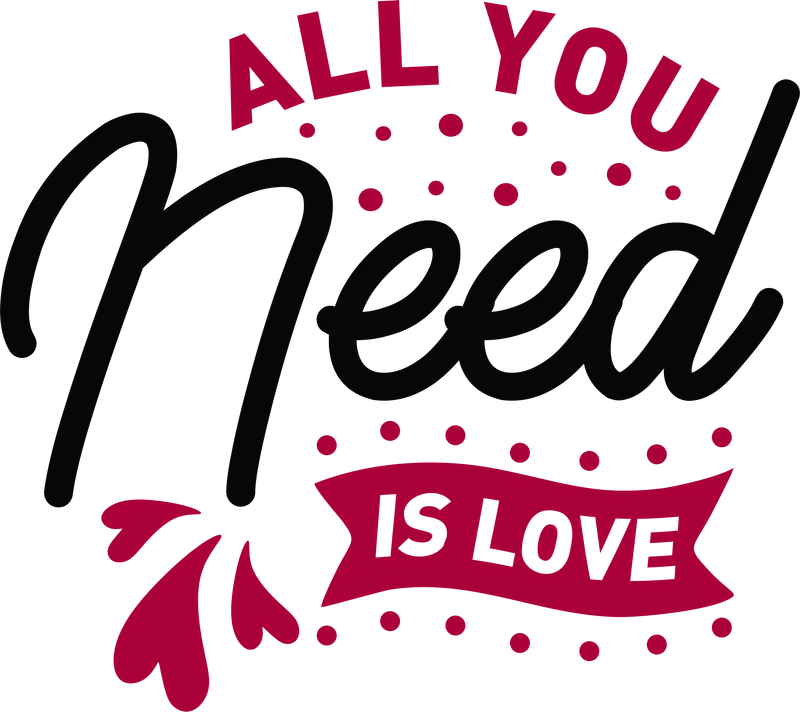
Thông điệp "All You Need Is Love" font chữ độc đáo
Thông điệp "All You Need Is Love" font chữ độc đáo — Thiết kế chữ "All You Need Is Love" độc đáo, truyền tải thông điệp ý nghĩa. Phù hợp in chuyển nhiệt lên áo, túi, quà tặng.
Trong hình có: chữ viết, slogan, biểu tượng trái tim
Phong cách: line-art · Cảm giác: yêu thương
Tông màu chủ đạo: xám, hồng